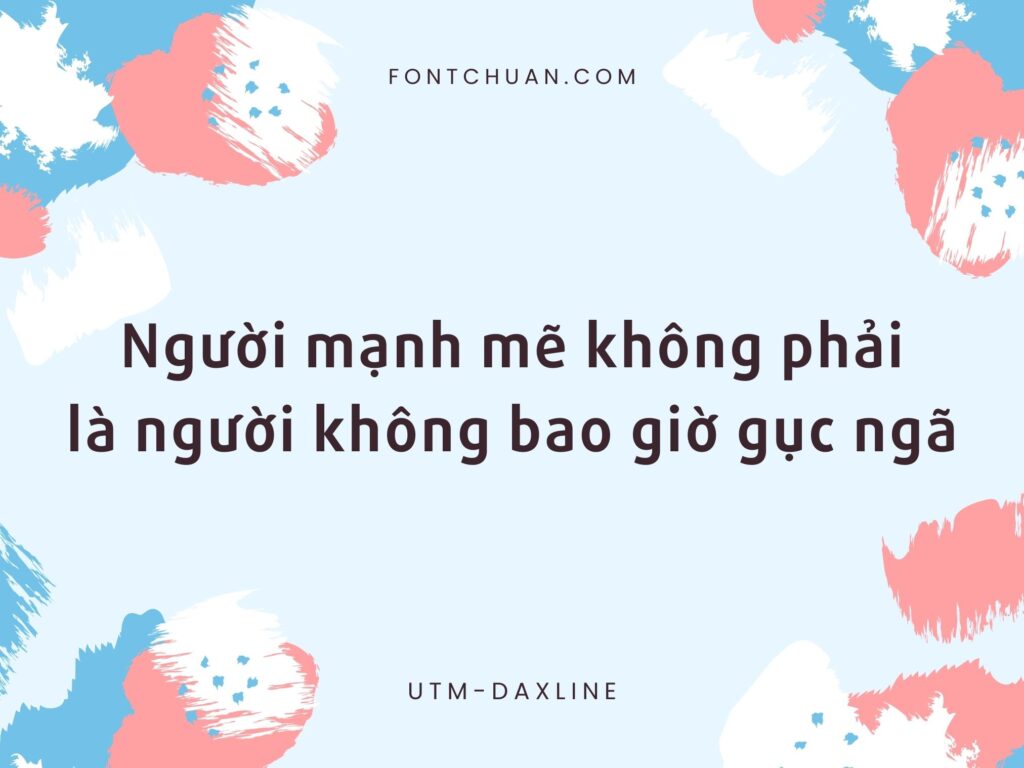
UTM Daxline là phiên bản Việt hóa của font chữ Daxline, một kiểu chữ sans-serif hiện đại được thiết kế bởi Hans Reichel. Font này nổi bật với các ký tự có đường nét đơn giản, gọn gàng và dễ đọc, tạo cảm giác chuyên nghiệp và thân thiện. Phiên bản Việt hóa đã được thực hiện bởi Unicode Thiên Minh, hỗ trợ đầy đủ tiếng Việt cùng hơn 100 ngôn ngữ khác. Đây là một trong những font được cộng đồng thiết kế sưu tầm và chọn lọc nhằm đáp ứng nhu cầu đa dạng trong thiết kế.
UTM Daxline có cấu trúc chữ với các nét thẳng và cong hài hòa, tạo nên sự cân đối và dễ nhìn. Font này phù hợp cho các ứng dụng như thiết kế tiêu đề, văn bản, logo, bao bì sản phẩm và các ấn phẩm in ấn yêu cầu sự hiện đại và tối giản. Các ngành nghề như quảng cáo, giáo dục, công nghệ và bất động sản có thể tận dụng UTM Daxline để tạo điểm nhấn độc đáo trong thiết kế.